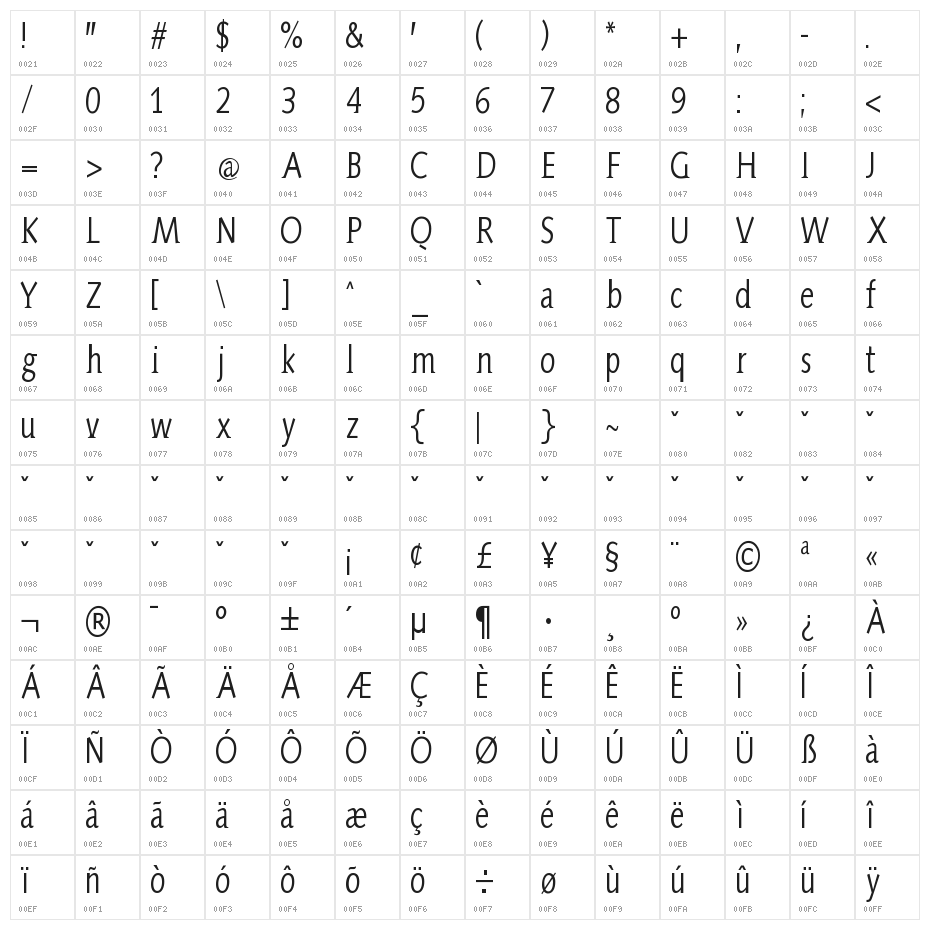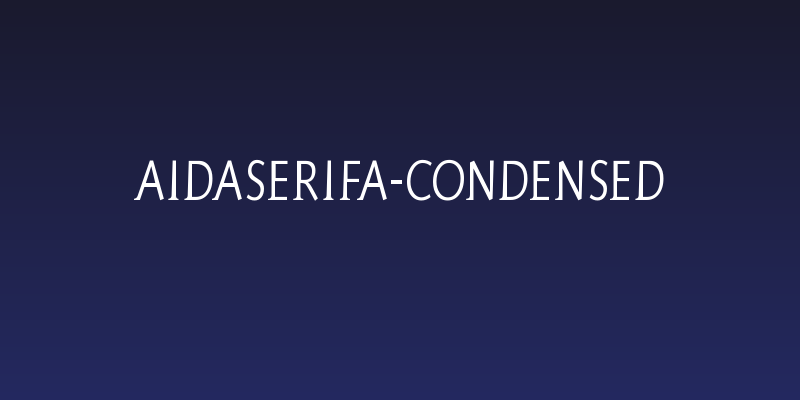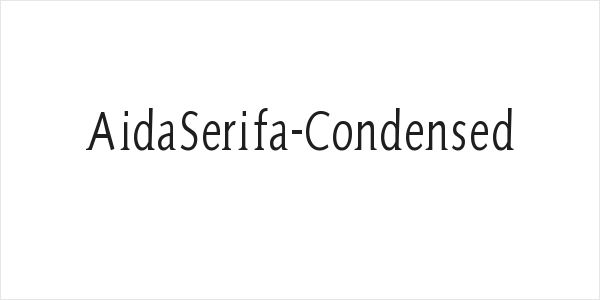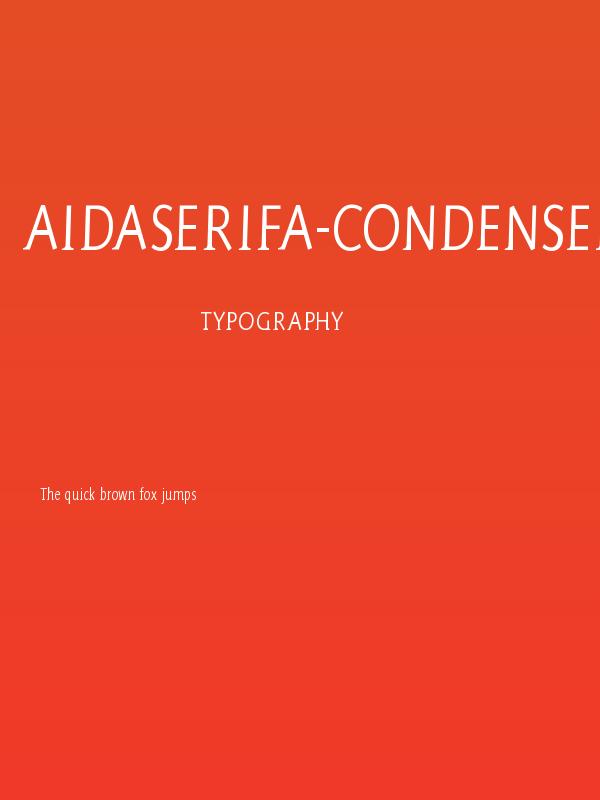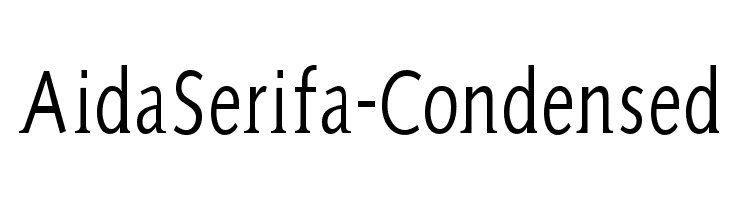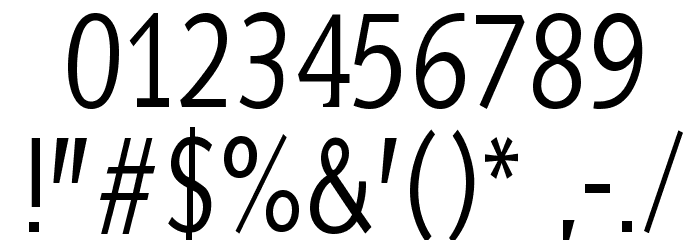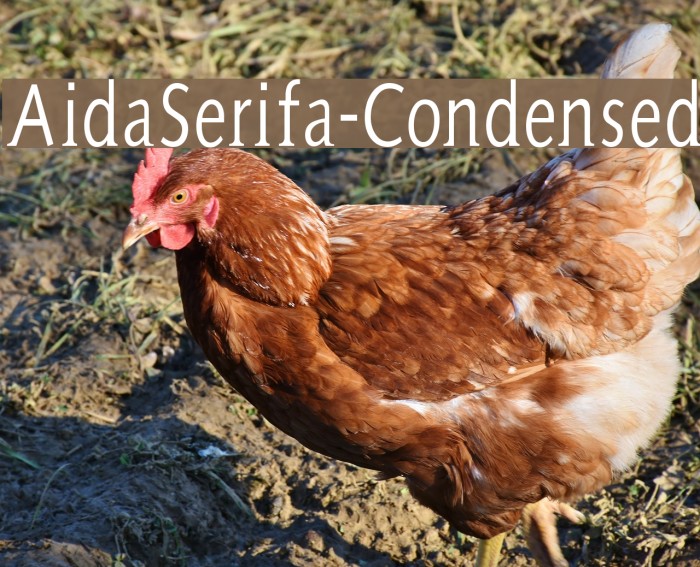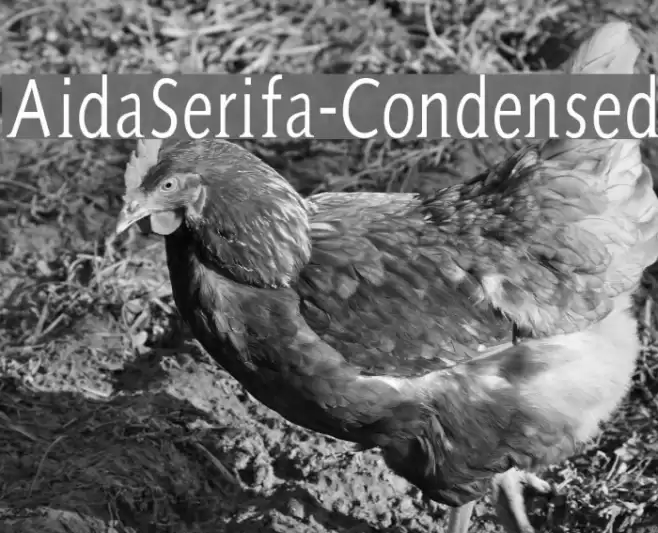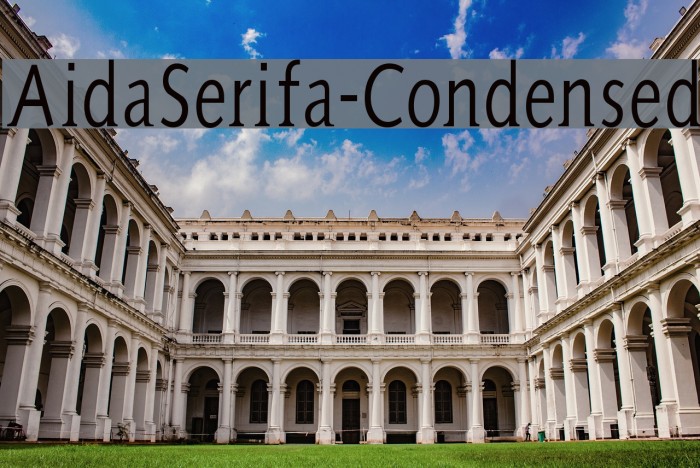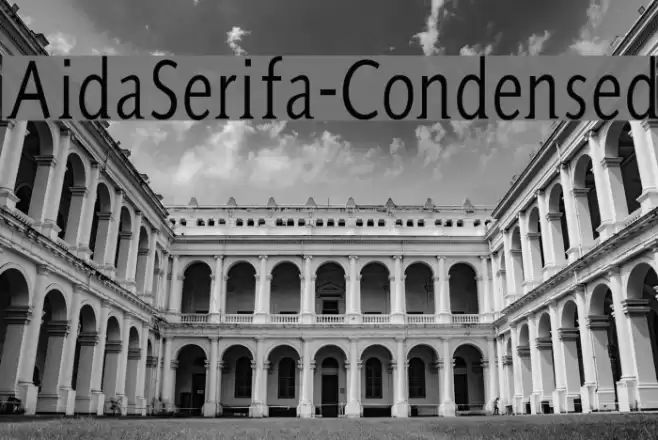
AidaSerifa-Condensed Font
| Gesamtstil | Classic |
| Anwendungsfall | Headlines, Body text, Logos |
| Vorgeschlagene Projekte | Ideal for editorial design, book covers, formal invitations, and corporate branding. |